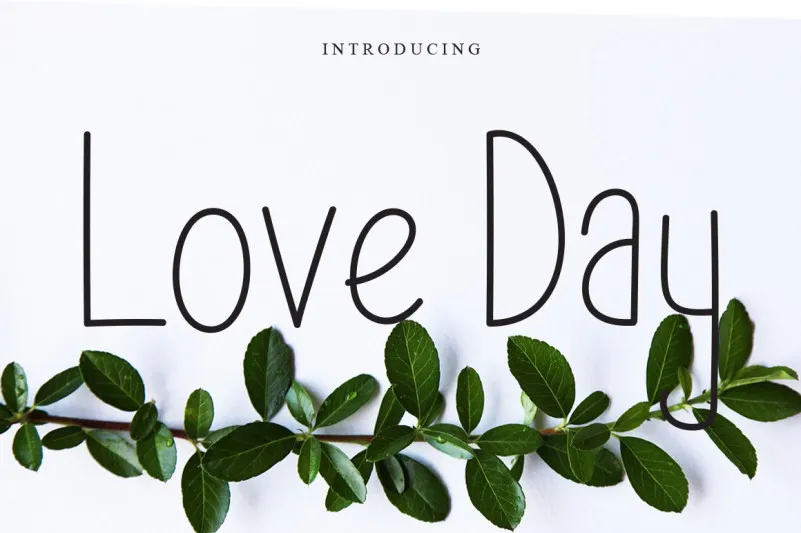
Love Day Font – Fonte Grátis
Love Day Font
Esta é uma fonte escrita à mão com traços finos e adaptáveis que traz uma leveza e delicadeza. É perfeita para aqueles desenhos que precisam de um toque romântico, seja para cartões personalizados ou pequenos detalhes em sua próxima arte digital. Independente do tópico, essa fonte se revelará como um elemento valioso na coleção de suas fontes digitais por seu poder de transformar qualquer criação num trabalho brilhante. Como o Designer LevinCreative a descreveu: “Esta é uma fonte escrita à mão delicada e adaptável. Sem importar do que seja, esta fonte será um imenso ativo para sua biblioteca de fontes digitais, pois tem potencial para elevar qualquer criação.” Esse design único traz a atmosfera suave e encantadora que faz com que seu projeto brilhe ainda mais.